Font Chữ Viết Tay Là Gì? Khi Nào Nên Dùng?
Font chữ viết tay (handwritten font) là nhóm phông chữ mô phỏng nét chữ viết bằng tay: có độ “ngẫu hứng”, cong mềm hoặc nét bút dày, tạo cảm giác thân thiện và cá nhân hóa. Bạn nên dùng font viết tay khi:
- Làm thiệp cưới, thiệp mời, thiệp chúc mừng
- Thiết kế poster, banner, ảnh bìa, story mạng xã hội
- Trang trí bullet journal, sổ tay, tiêu đề bài học
- Thiết kế bao bì, nhãn sản phẩm handmade, sticker
- Tạo điểm nhấn cho typography (tiêu đề, quote, chữ trang trí)
Một Số Font Chữ Viết Tay Đẹp Việt Hóa Đẹp
Taimienphiday.com chia sẻ một số font chữ viết tay đa phong cách, phù hợp làm thiệp cưới, banner, notebook, thiết kế mạng xã hội và in ấn:
Font Viết Tay Dễ Thương (Cute)
Hợp thiết kế sticker, sổ tay, bài đăng nhẹ nhàng, sản phẩm handmade.
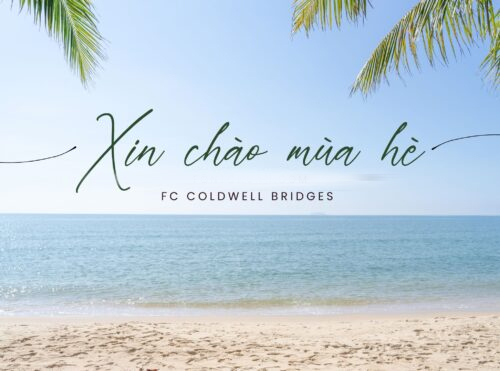
Font Viết Tay Tối Giản (Minimal)
Dễ đọc, hợp caption, tiêu đề bài học, slide thuyết trình.
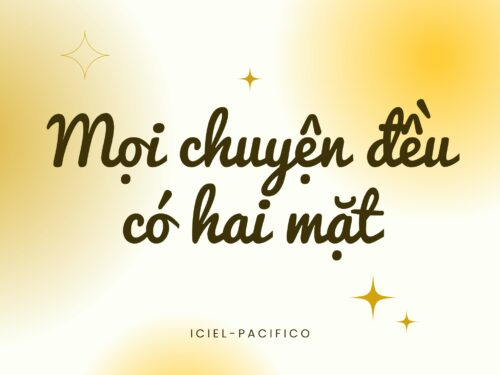
Font Viết Tay Vintage
Tạo cảm giác hoài cổ, phù hợp ảnh film, poster retro.
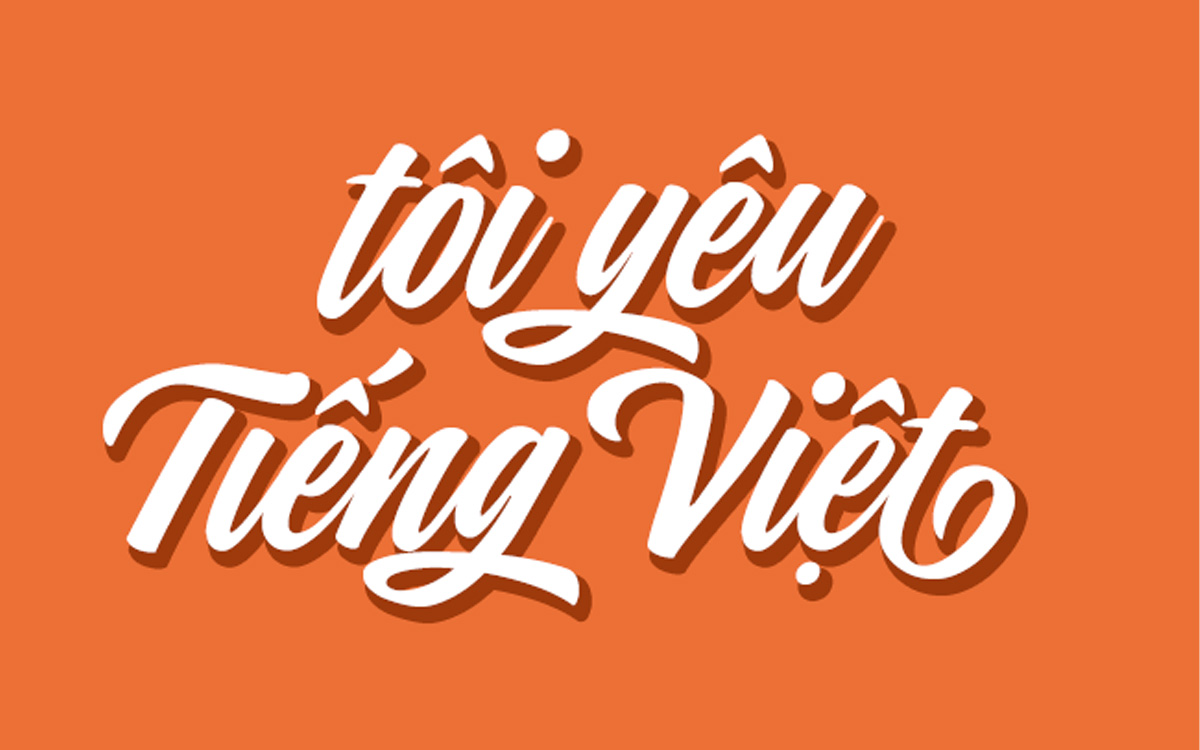
Font Viết Tay Marker/Brush (Nét bút dày)
Nổi bật khi làm banner, headline, typography mạnh.
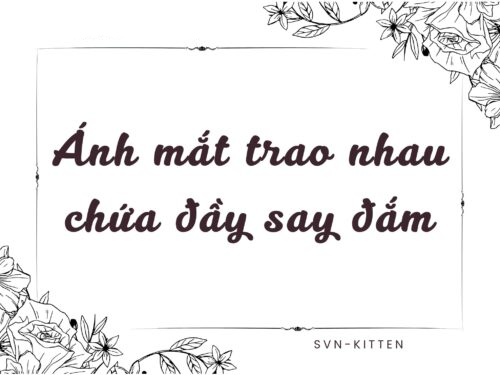
Font Viết Tay Cho Thiệp Cưới
Mềm, thanh lịch, hợp tên cô dâu chú rể, lời mời.
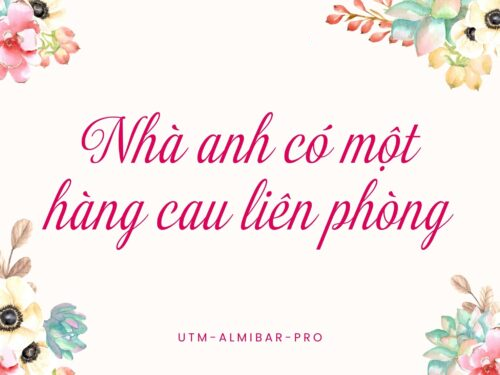
Font Chữ Ký Viết Tay (Signature)
Hợp watermark, logo chữ, chữ ký cuối ảnh.